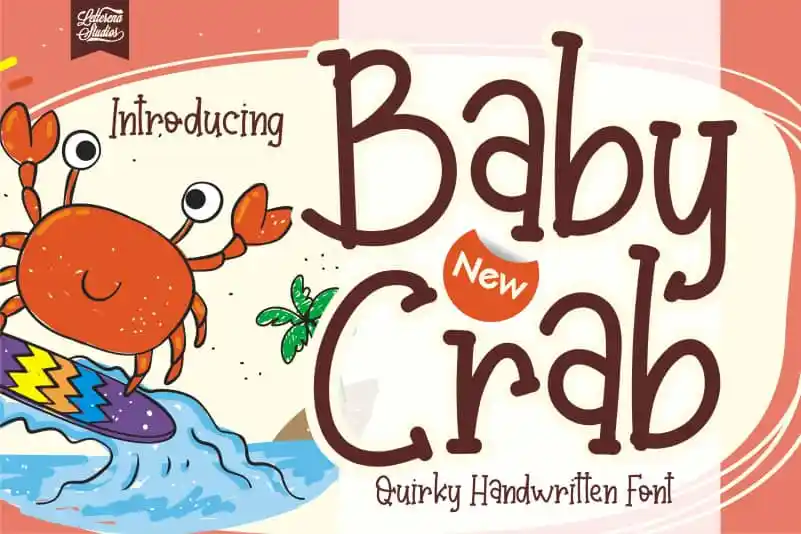
Baby Crab Display Font – Download Grátis
Baby Crab Display Font é uma fonte escrita à mão com um estilo inovador. Ela apresenta uma aparência descontraída e autêntica que certamente cativará qualquer criativa buscando aperfeiçoar seu próximo projeto DIY. Essa elegante tipografia não apenas enriquecerá seus projetos, mas também os tornará únicos. Através de Baby Crab Display Font, você pode transformar qualquer tarefa em uma experiência divertida e inspiradora, permitindo que suas ideias fluam com fluido entusiasmo. Seja para criar um lembrete personalizado ou decorar uma decoração, essa fonte é perfeita para quem quer dar vida a seus projetos de forma vibrante e inovadora.